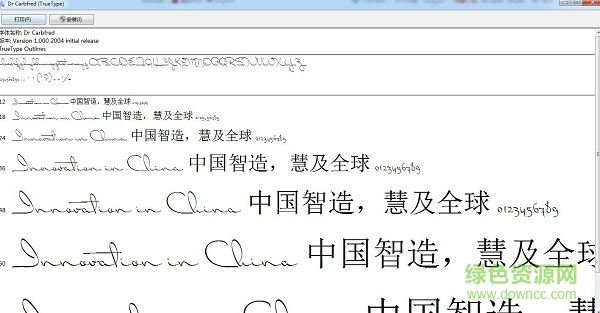
drcarbfred
dr carbfred字體是一款漂亮的英文藝術(shù)字體,字形張揚(yáng),裝飾意味強(qiáng),適用于商品包裝、影視海報(bào)以及各類廣告中,效果非常棒,歡迎大家免費(fèi)下載!
藝術(shù)字體介紹
藝術(shù)字體是字體設(shè)計(jì)師通過對中國成千上萬的漢字,通過獨(dú)特統(tǒng)一的變形組合,形成有固定裝飾效果的字體體系,并轉(zhuǎn)換成ttf格式的字體文件,用于安裝在電腦中使用,這樣才可以叫做藝術(shù)字體。